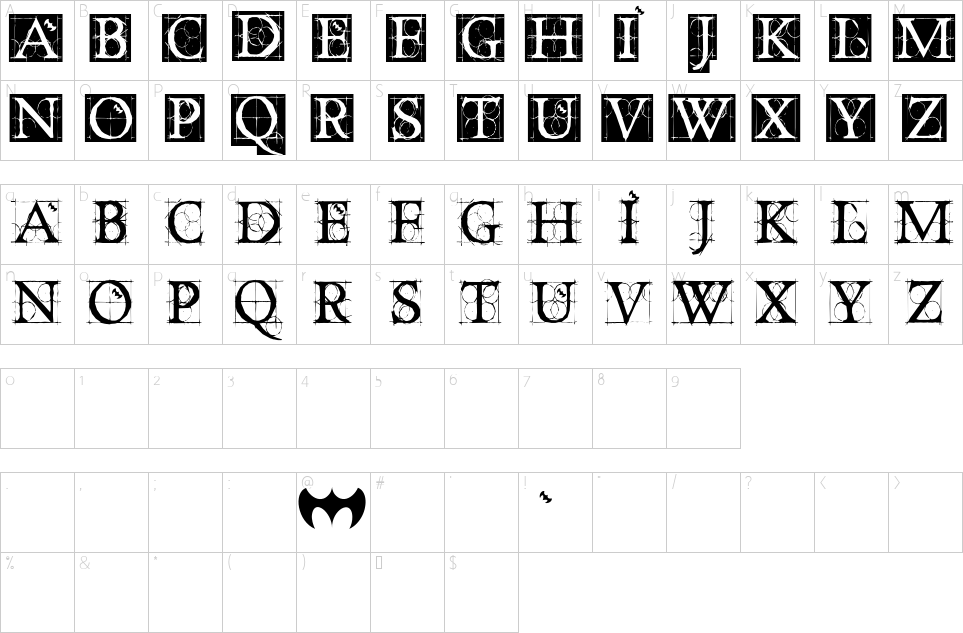
Dancing Vampyrish Font – Download Grátis
Descubra a dança sinistra e vampiresca que é Dancing Vampyrish Font, uma elegante e intrigante escolha para adicionar um toque único às suas criações digitais. Desenvolvida pelo talentoso designer Manfred Klein 凌, essa fonte oferece uma paleta de caracteres que parece pulsação rápida do coração em meio à tempestade, ideal para criar texturas intensas e narrativas atraentes. Os usuários já descarregaram mais de 7.800 vezes esta fonte para seus projetos de design gráfico, arte digital e criações digitais. Se você está procurando por uma fonte que pode capturar o seu público com sua personalidade vampirica, Dancing Vampyrish Font é a escolha perfeita. Descubra agora como ela pode dar vida a sua próxima obra!